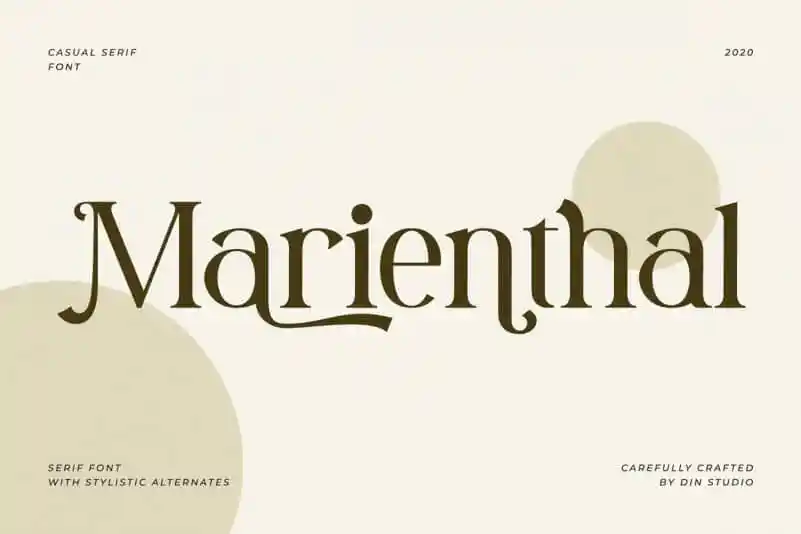
Marienthal Serif Font
A Marienthal Serif é uma fonte serif que se destaca por sua mistura moderna e clássica. Desenvolvida pela Din Studio através do site 99designs, ela traz à tona um toque vintage ao mesmo tempo que revela uma elegância contemporânea. Perfeita para projetos de identidade visual profissionais, a Marienthal serif é ideal tanto para marcações e impressões comerciais quanto para decoração de eventos como casamentos ou gravações de vida. A fonte é cuidadosamente elaborada para que cada letra seja única e apresente um toque sofisticado característico do gênero serif, tornando-a uma escolha inigualável para qualquer projeto onde se deseja transmitir estilo e elegância.